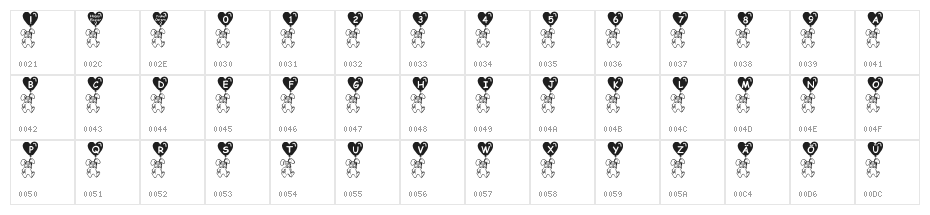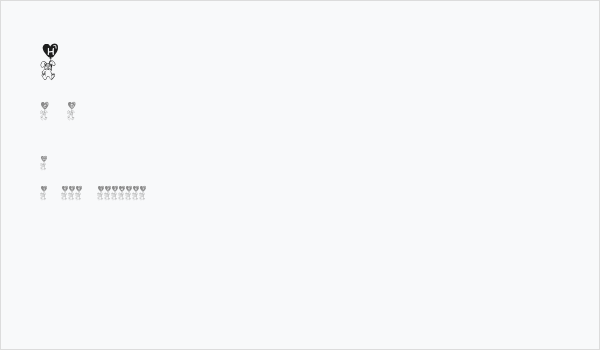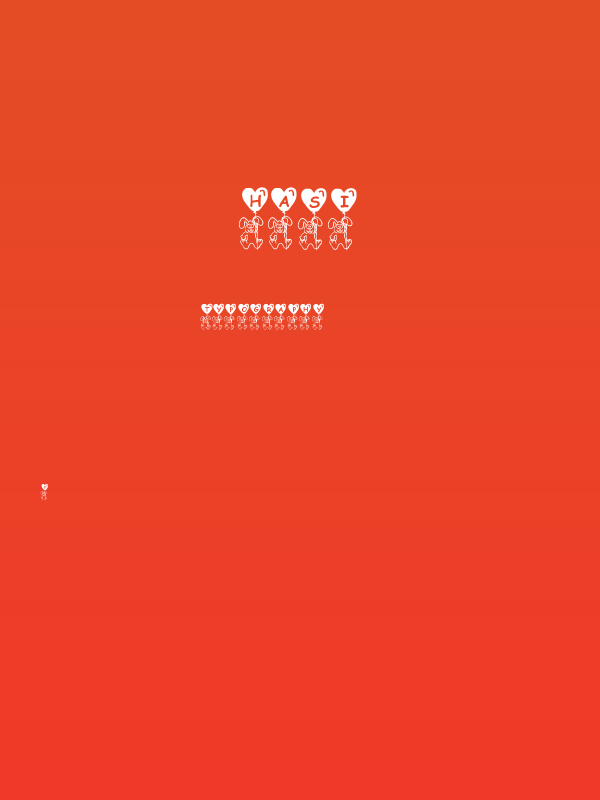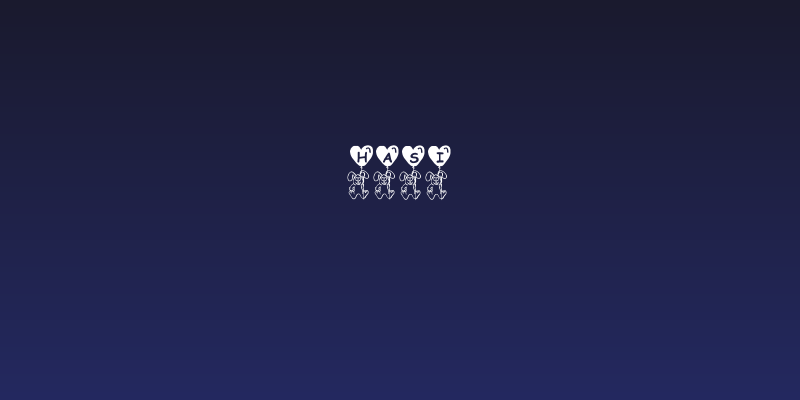
Hasi Font
| Caso d'uso | Headlines, Logos, Event Invitations |
| Progetti proposti | Ideal for Easter cards, children's party invitations, festive banners, and playful branding. |